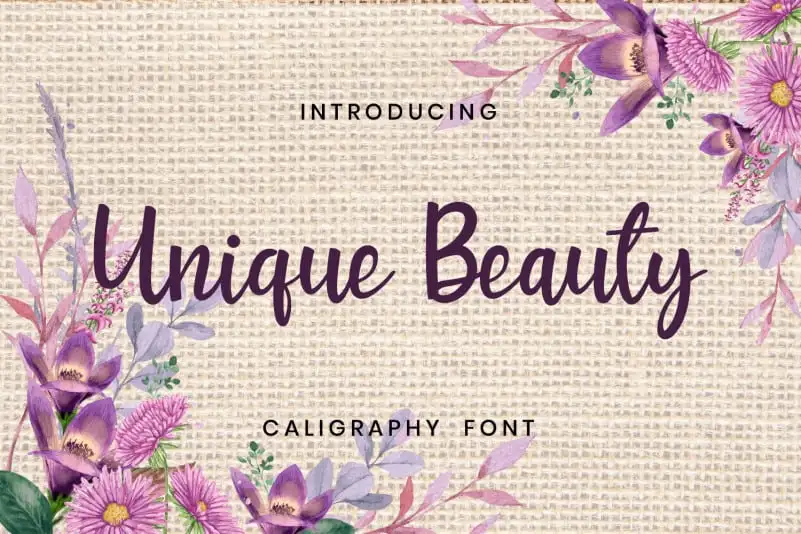
Unique Beauty Script Font – Download Grátis
A fonte ‘Unique Beauty Script Font’ é uma elegante e fluida escrita à mão criada com a ajuda de uma caneta-pen. Perfeita para aqueles que buscam um toque único e sofisticado em seus projetos, essa fonte será o complemento perfeito para qualquer design. Suas linhas delicadas e estilo elegante fazem dela uma escolha ideal para criações personalizadas ou profissionais. Através da ‘Unique Beauty Script Font’, sua identidade visual ganhará profundidade e originalidade, tornando-a um elemento inconfundível em qualquer projeto de design. Sinta-se à vontade para explorar as possibilidades criativas dessa fonte única e encantadora.